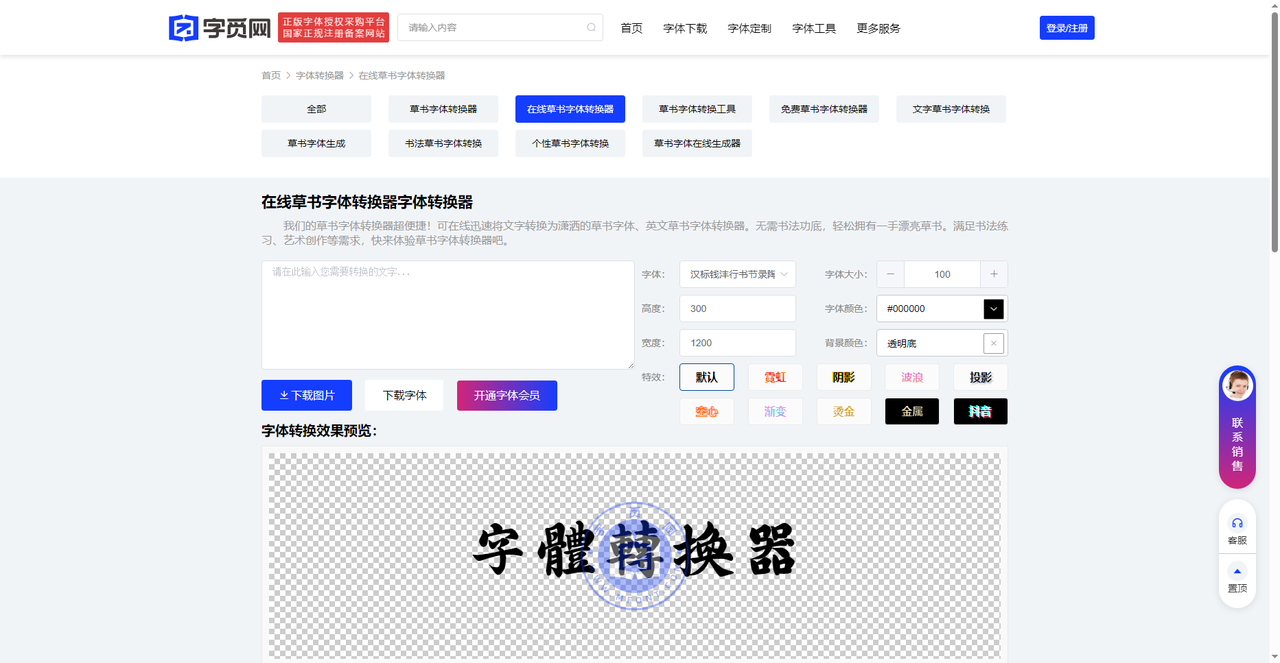
草书字体不用愁,这几个转换器让你秒出效果
草书是中国书法中最奔放、最自由的字体,笔画连绵、结构简省。但想做一张有书法味的海报、一个古风Logo,怎么办?不用请书法家,也不用自己苦练,在线草书转换器就能帮你。输入简体汉字,选择不同的草书风格,几秒钟就能生成草书图片。今天整理了5款草书转换工具,有正版字体库、有特效调节、有多风格选择,从设计师到普通用户都能用。
字由是国内最大的字体管理与AI平台之一,它收录了多款正版草书字体,适合专业设计师使用。打开字由客户端或网页版,在搜索栏输入“草书”,或者在字体类型中筛选“书法体”再找“草书”,就会出现丰富的草书字体列表。
字由还提供了在线预览功能:在字体详情页输入你自己的文案,可以实时看到这款字体的实际效果,不用激活就能判断是否合适。对于需要长期、反复使用同一款草书字体的品牌项目,字由是最专业的选择。
第二个网站是字页网的正版字体授权采购平台旗下的“在线草书字体转换器”。它的功能非常全面,不仅有转换功能,还能添加各种特效。页面中央是一个大的输入框,输入你想要转换的文字。设置完成后,点击“下载图片”即可获得转换后的草书图片。网站还提供了“下载字体”“开通字体会员”等商业授权入口。对于想要快速做出有特效的草书标题的用户来说,字页网很方便。例如,你可以做一个霓虹灯效果的草书标题,或者烫金效果的草书Logo。
第三个网站是一个草书转换软件平台。它提供了多种草书转换选项,包括“转换为草书”按钮,以及大量草书作品欣赏和知识文章。操作方法:在上方输入框输入汉字,点击“转换为草书”按钮,下方就会展示转换后的草书图片。页面还附带了丰富的草书杂谈、书法欣赏、名家作品等内容,例如“王羲之笔下最美的36个字”“赵孟行书欣赏”等。对于书法爱好者和初学者,这个站既是工具也是学习平台。转换结果图片可以右键保存。虽然它的特效调节不如字页网丰富,但胜在简单直接,并且有浓厚的文化氛围。如果你不只是想转换几个字,还想了解草书的历史和技法,这个站值得多翻翻。
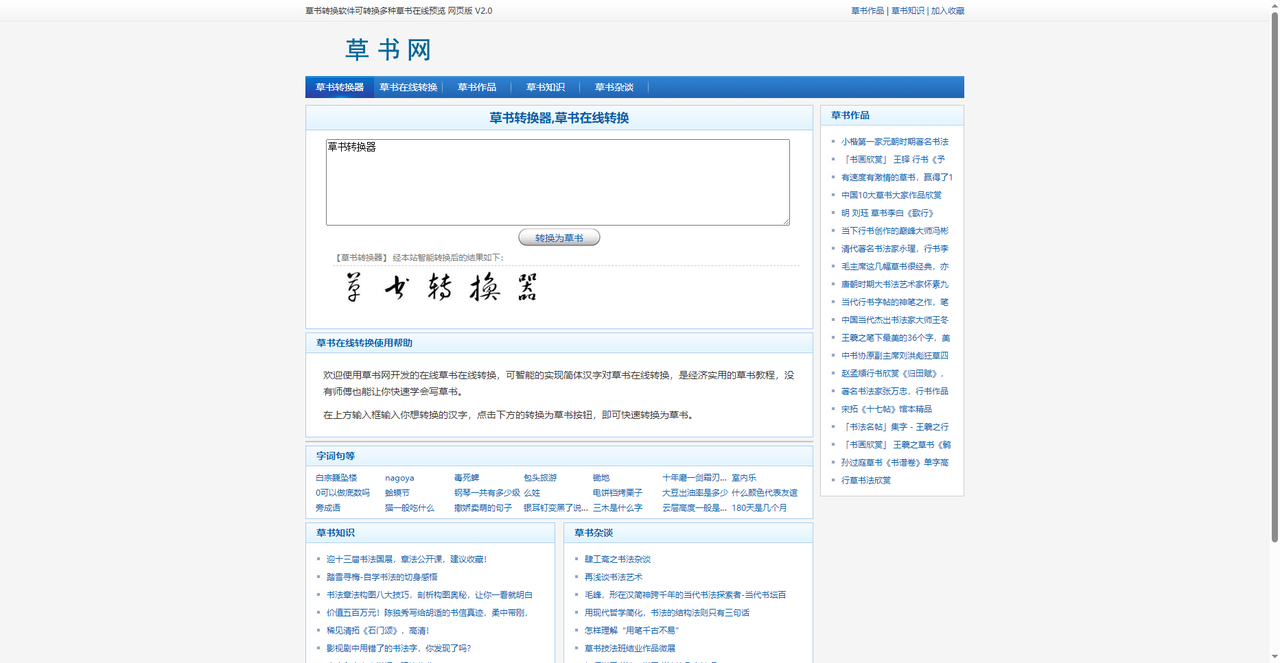
第四个网站是字体转换网的“草书字体转换器”。它提供了多种草书风格选项,点击不同的按钮,可以转换出不同风格的草书效果。其中最特别的是“毛泽东草书字体转换”——毛主席的草书独树一帜,气势恢宏,很多设计师喜欢用这种风格做红色主题或怀旧风格的海报。此外,页面还介绍了草书的基本常识:章草、今草、狂草的区别,以及代表作品。使用方法很简单:输入文字,点击相应的转换按钮,结果以图片形式展示。可以下载或截图保存。这个站适合需要特定风格草书(如毛体)的用户。
第五个网站是一个草书字体生成器(截图中的第四张图)。它提供了丰富的草书字体选择,包括:
- 叶根友刀锋黑草
- 良怀衍草
- 福效律草
- 良怀行草
每款字体都带有预览效果。用户可以在输入框中输入文字,选择想要的字体,调节字体下色、上色、背景、大小、倒影、渐变、投影等参数,点击“点击生成”按钮即可输出图片。这个站的字库非常丰富,几乎涵盖了市面上常见的草书字体风格,既有叶根友等知名设计师的作品,也有方正狂草等经典。该站还提供了醒目的警示:“转换字体结果不能做为商业用途,商业用途请至字体厂商购买正版授权。”所以适合个人学习、灵感参考,商用需要另行购买授权。如果你喜欢“叶根友刀锋黑草”这种现代感较强的草书,或者“方正狂草”这种传统狂草,这个站是最好的预览和转换工具。
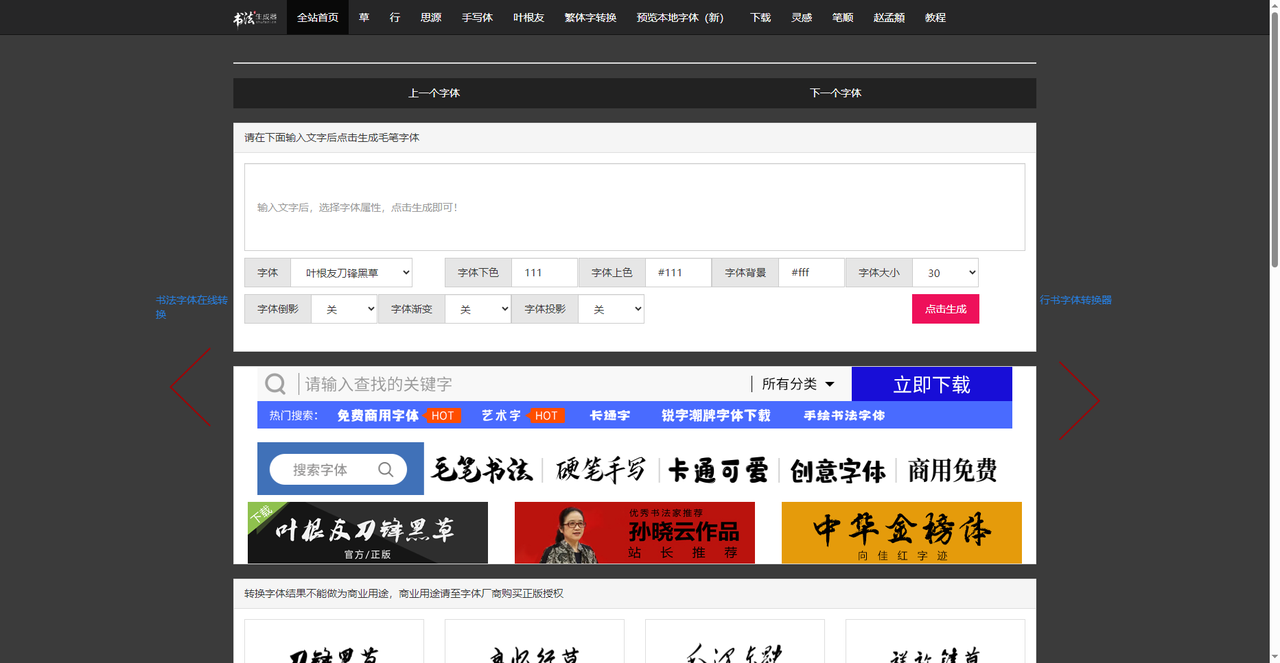
五款草书转换工具,字由最适合专业设计师,提供点字文人榜书、汉仪苏泽立行楷等正版商用草书字体;字页网支持霓虹、烫金、金属等多种特效,可下载带效果的高清图片;草书转换软件附带大量书法知识和作品欣赏,适合学习参考;字体转换网提供毛泽东草书等特色转换选项;最后一个草书生成器字库最全,涵盖叶根友刀锋黑草、方正狂草等几十款字体,可调节多种参数。输入你想转换的文字,选一款喜欢的草书风格,无论是做海报、写签名,还是学书法,总有一个工具能帮你打出写不出来的草书字体。